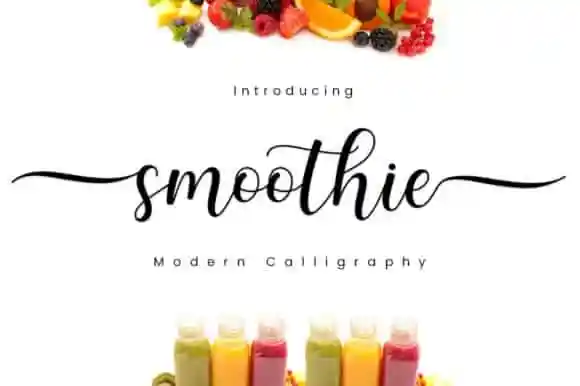
Smoothie Calligraphy Font – Download Grátis
A Smoothie Calligraphy Font é uma fonte script que traz uma sensação suave e encantadora a qualquer projeto gráfico. Essa elegante fonte foi criada pelo Manjalistudio e pode ser usada com sucesso no design de cartões de casamento, cartões de agradecimento, cartazes de citações, cards de presentes de felicitações, logomarcas, cartões de negócios e em qualquer projeto gráfico que precisa do toque handwritten especial. Suave e encantadora, ela torna seu próximo projeto ainda mais bonito e profissional. Engane-se para pensar nas cartas de agradecimento ou nas letras das citações em um anúncio de casamento; a fonte Smoothie é o que você precisa. Não espere, faça seu próximo design brilhar com essa suave e encantadora fonte script.